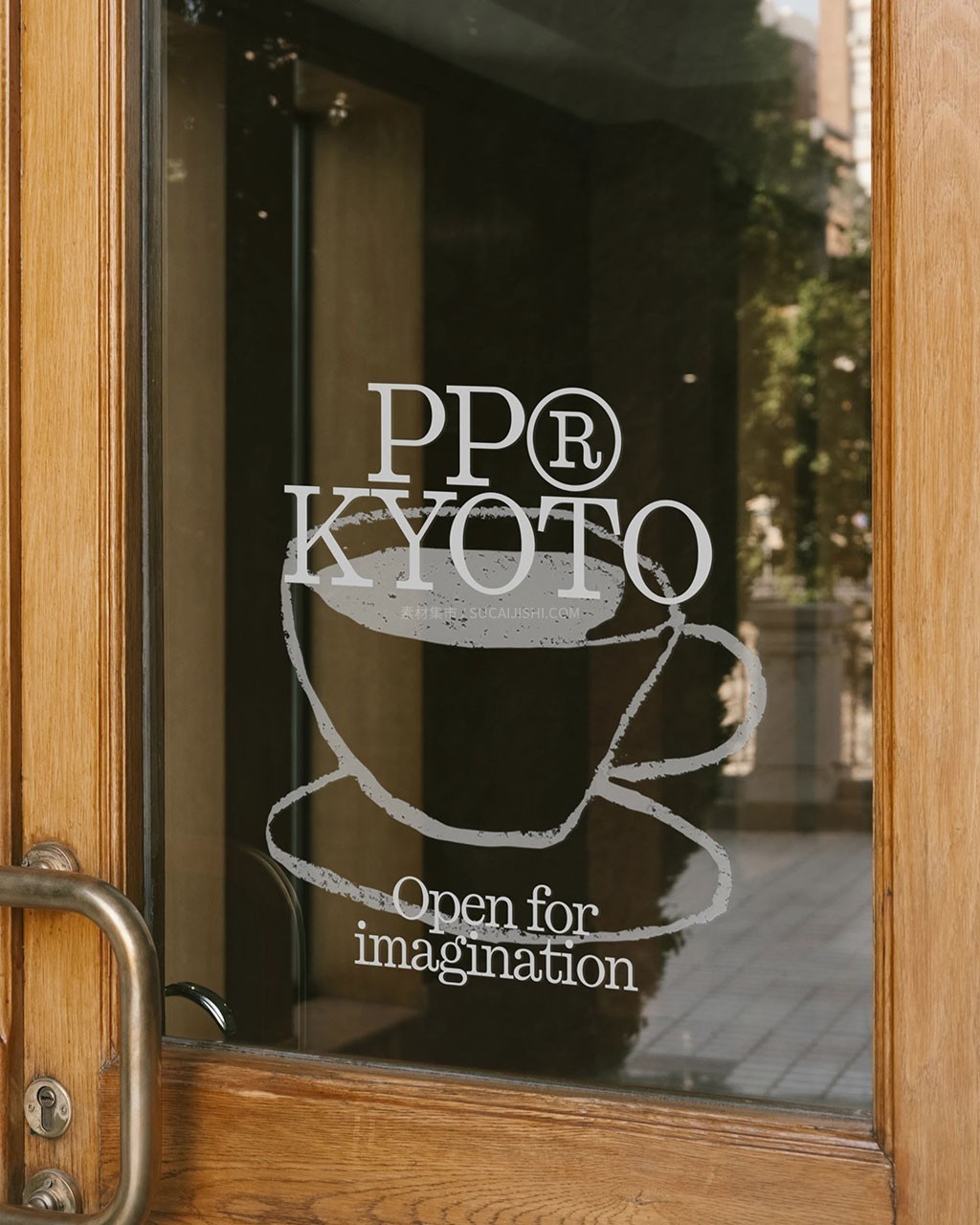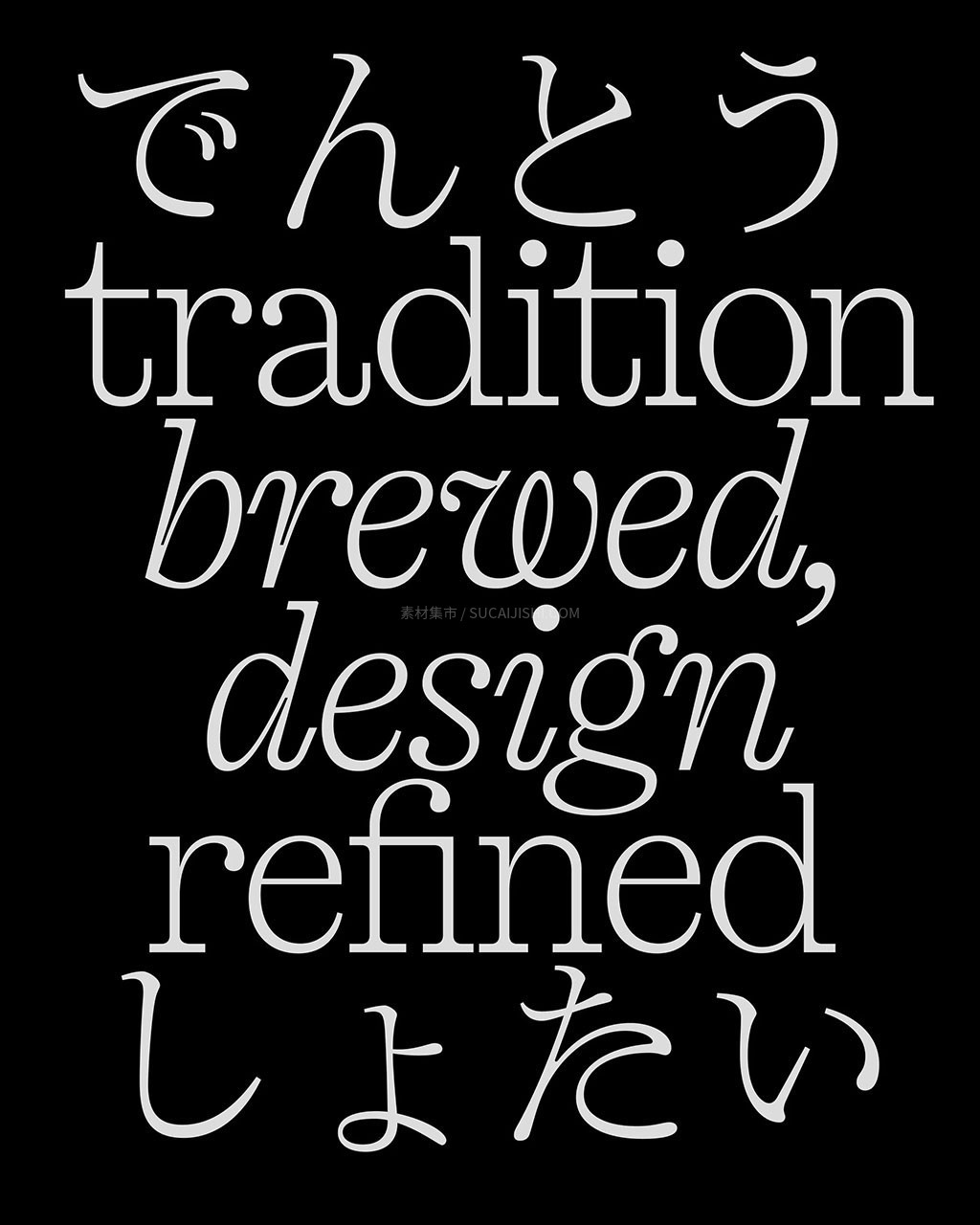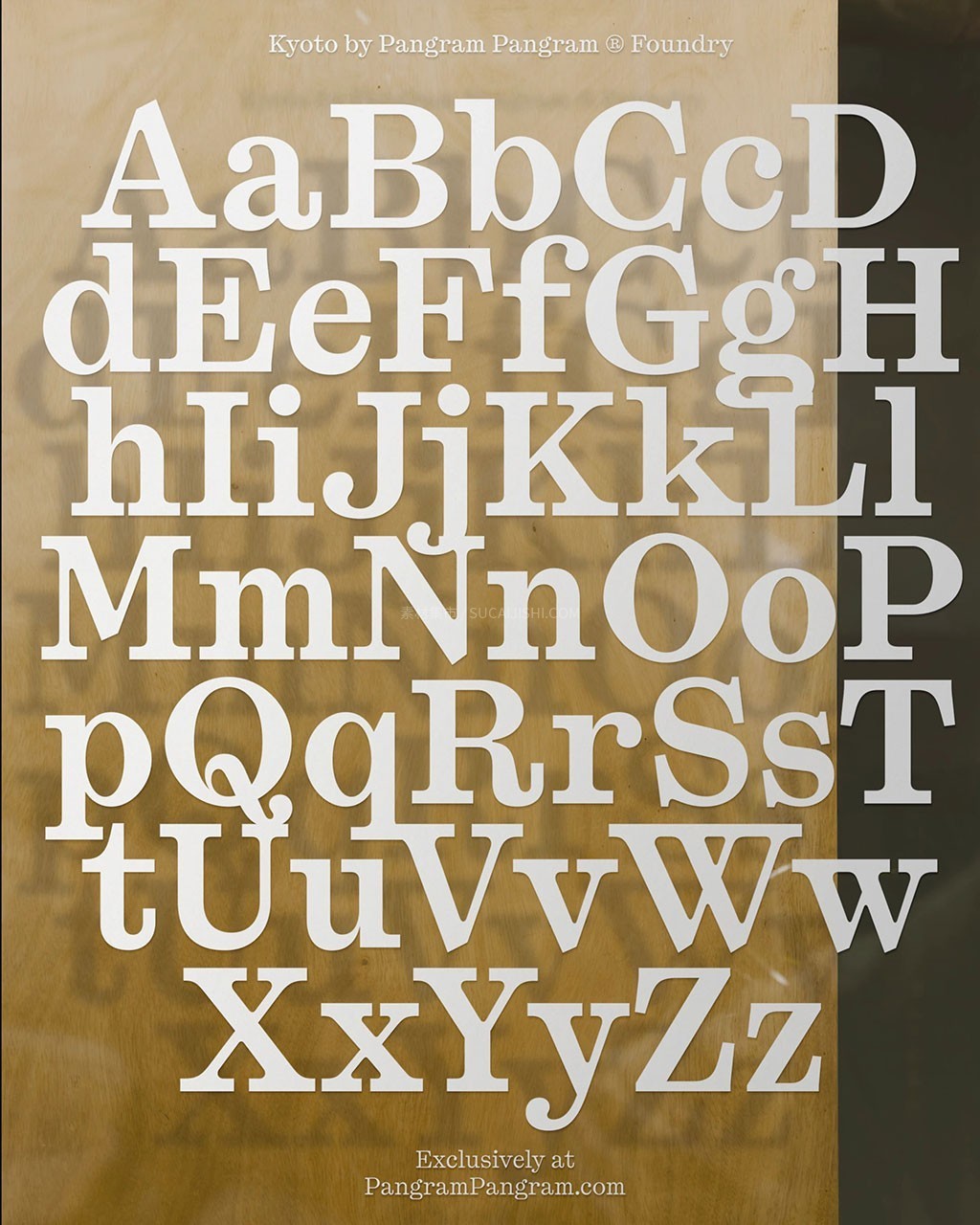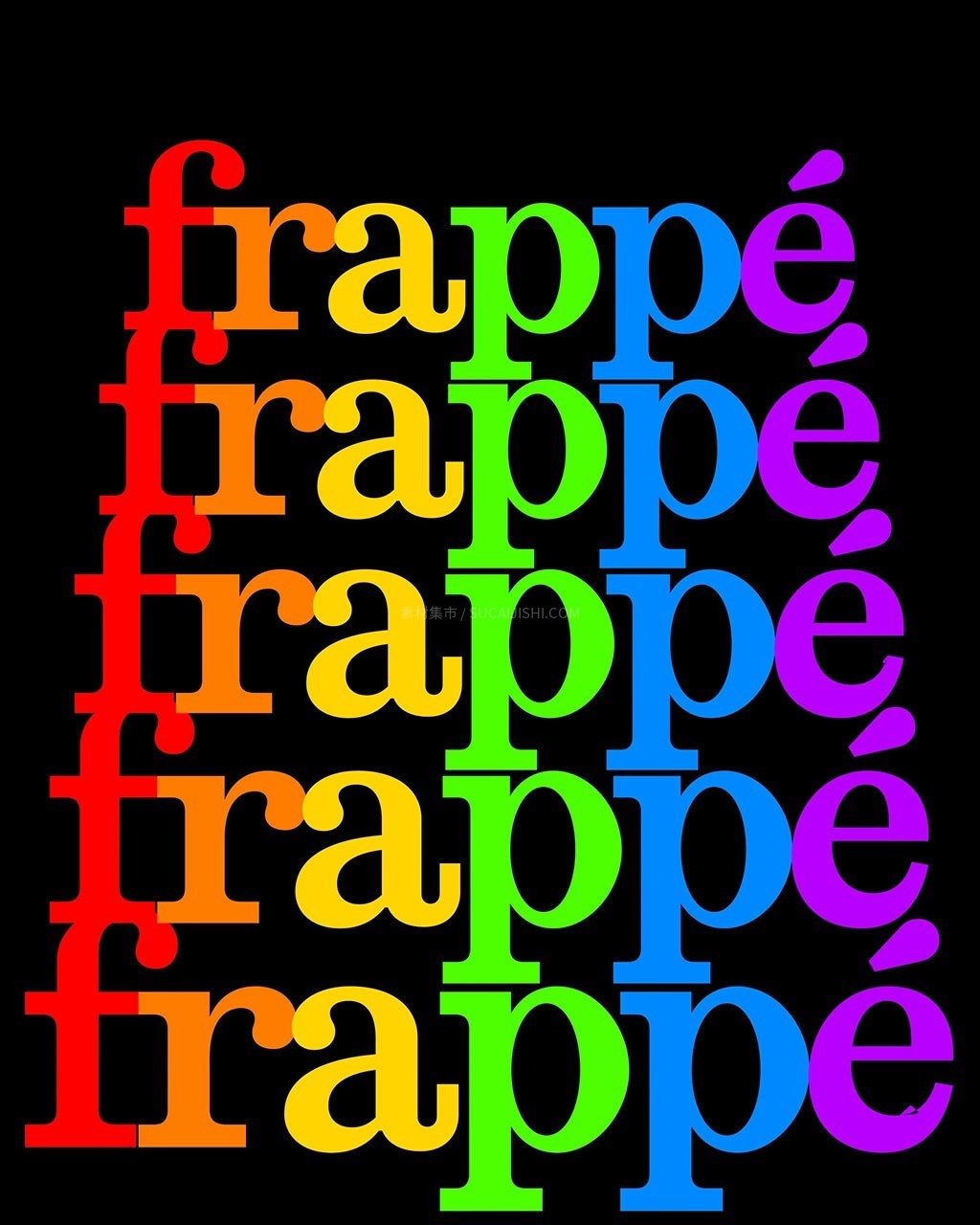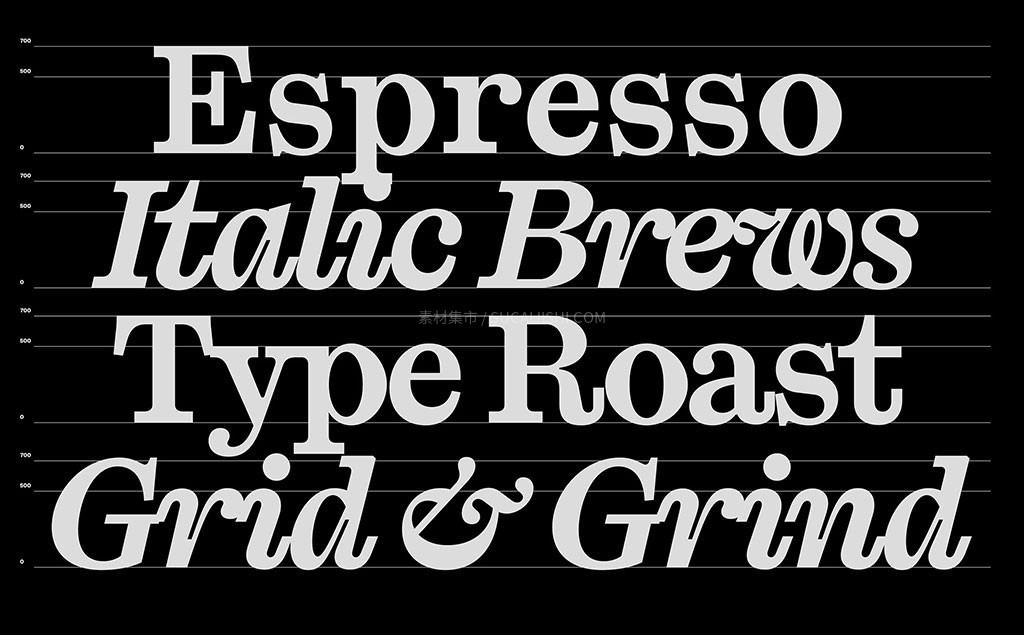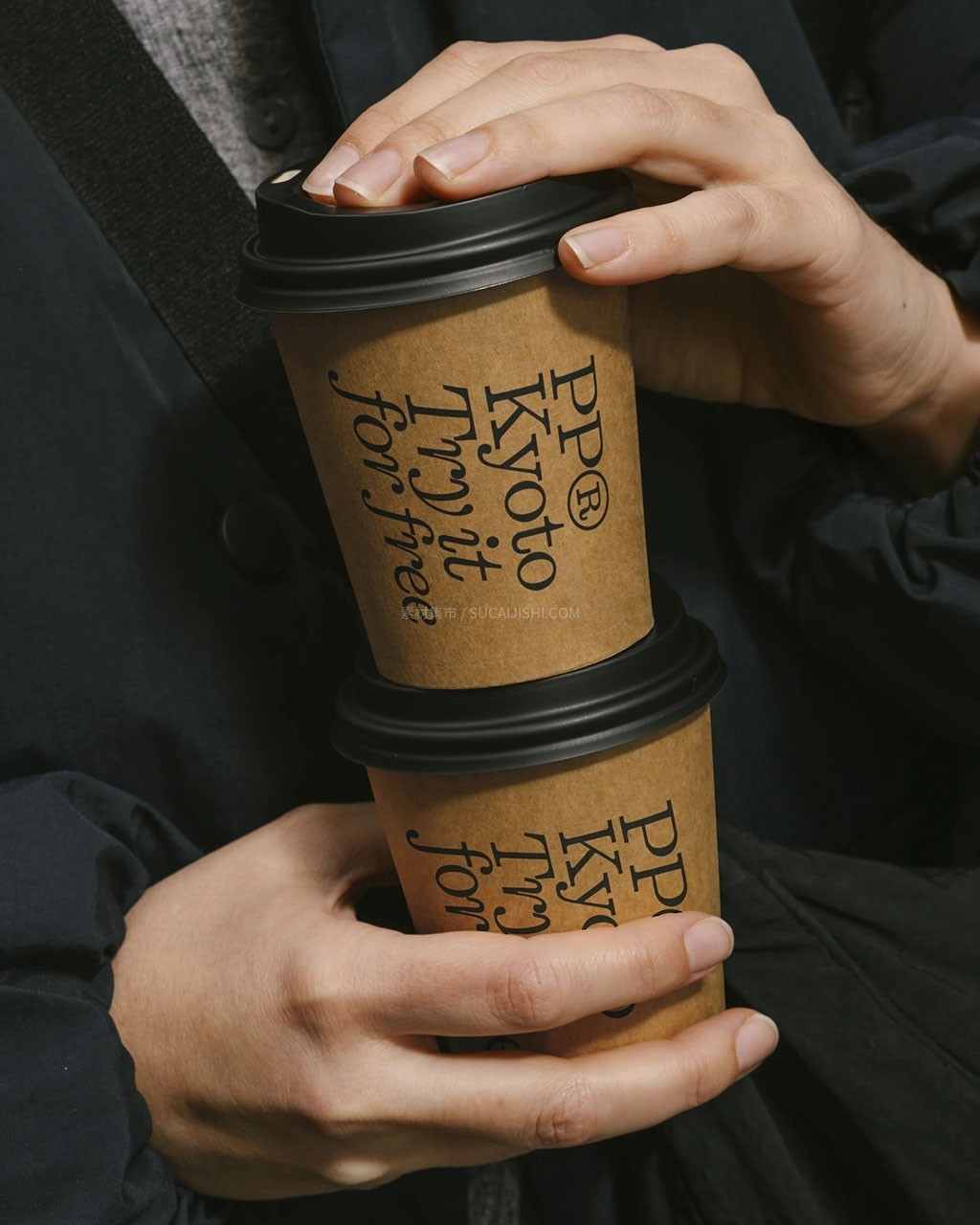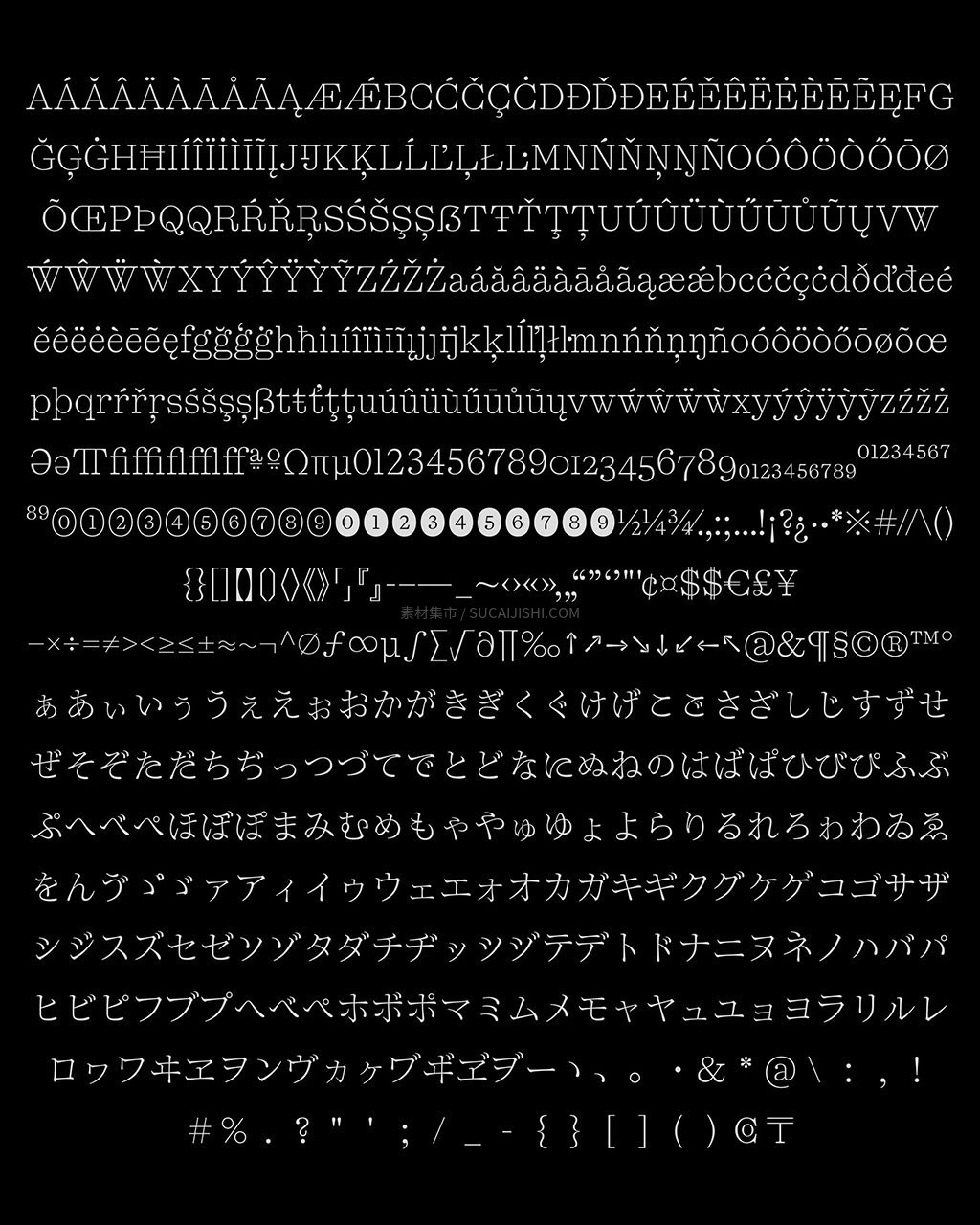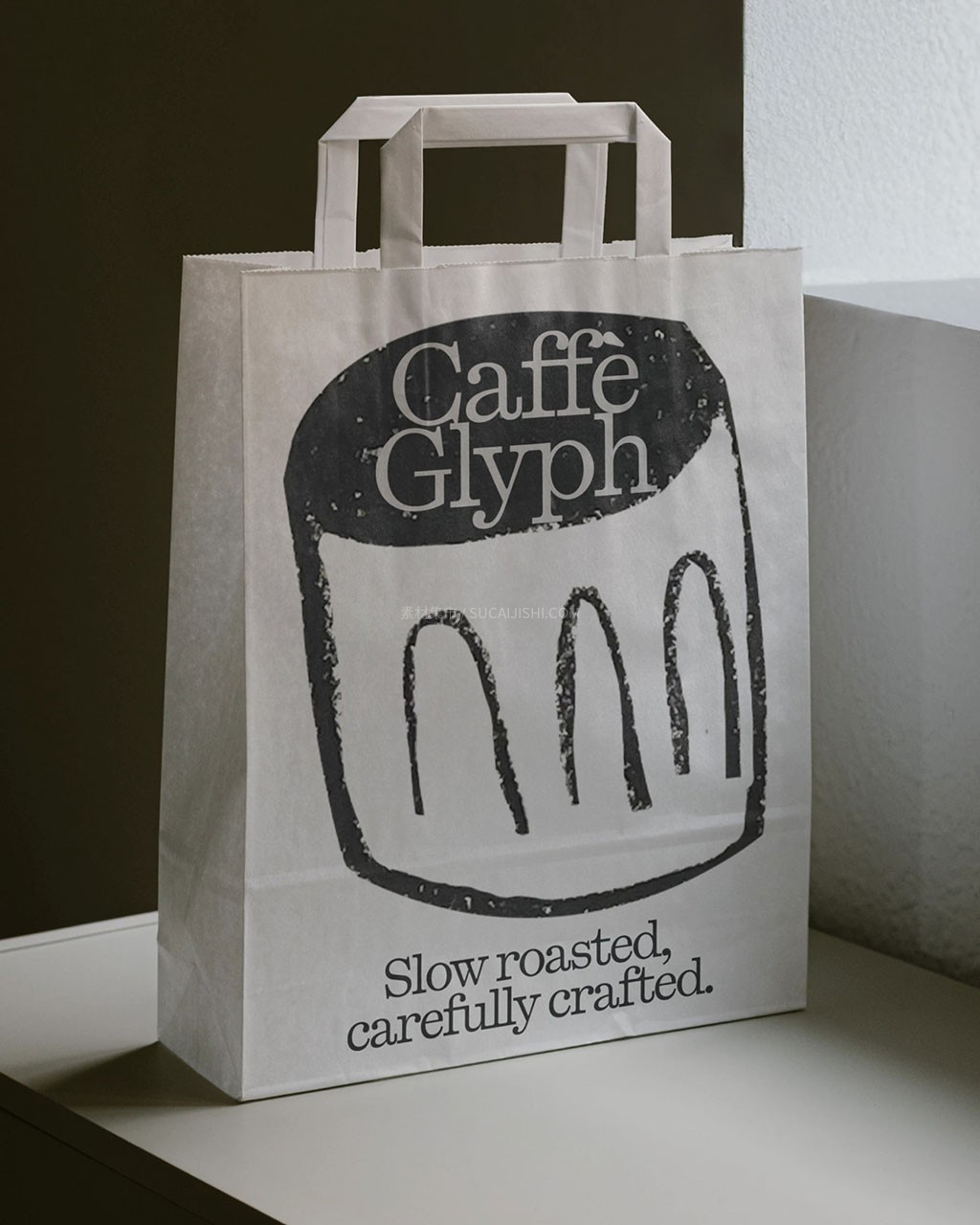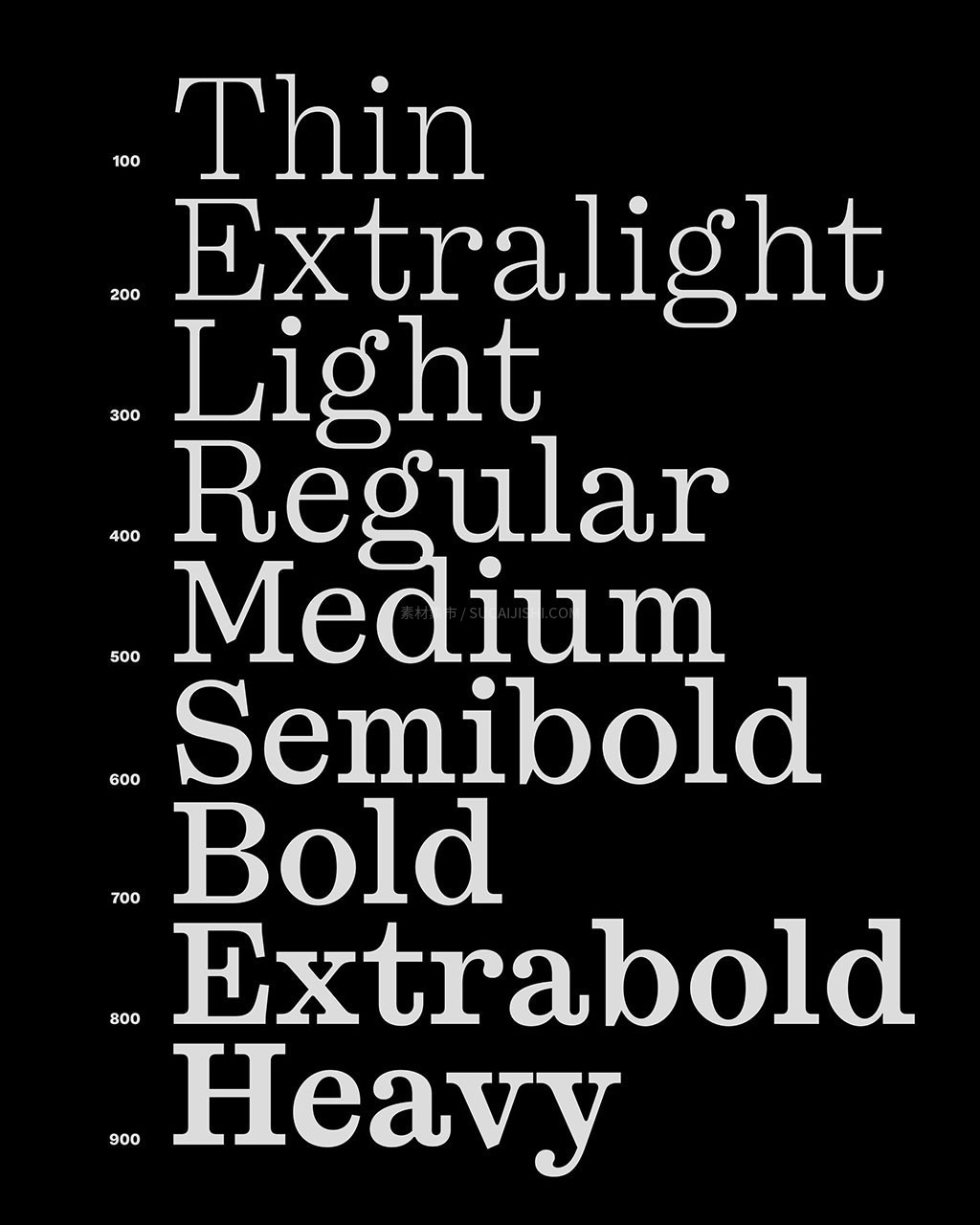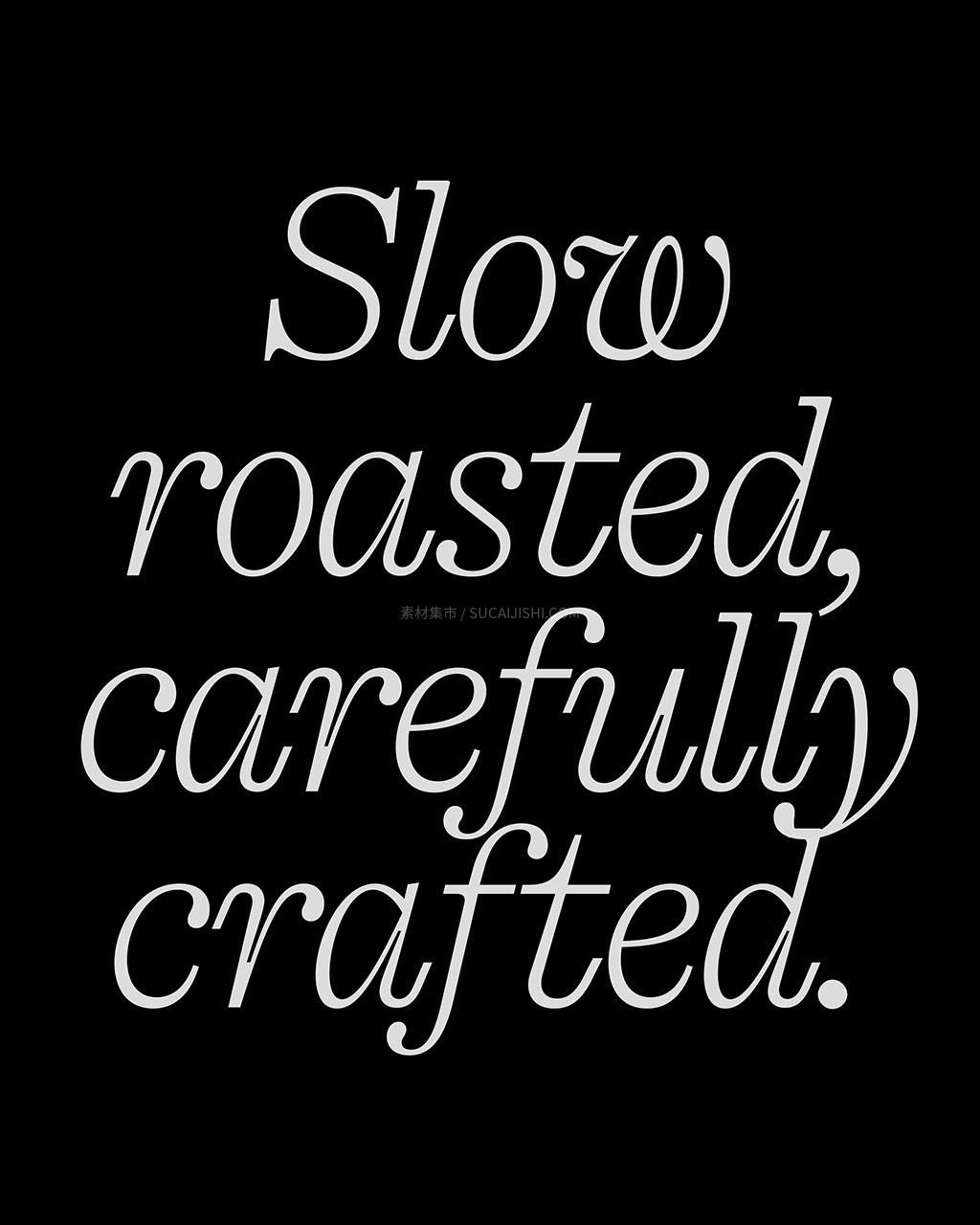
PP Kyoto 多语种粗衬线日文字体
PP Kyoto 是由知名字型厂牌 Pangram Foundry 推出的一款兼具传统与现代美学的全新粗衬线(Slab Serif)字体。专为醒目排版而生,巧妙融合了大胆的衬线结构与柔和的泪滴状笔画末端,让排版极具节奏感与表现力。字体共包含从 Thin 到 Heavy 的 9 个字重及对应斜体(共 18 种样式、692 个字形)。其核心亮点在于完美支持完整的拉丁字母、平假名、片假名及精细考量的日文标点符号,并内置丰富的连字、老式数字与多样式替换字符,是处理双语及多语种排版的绝佳利器。